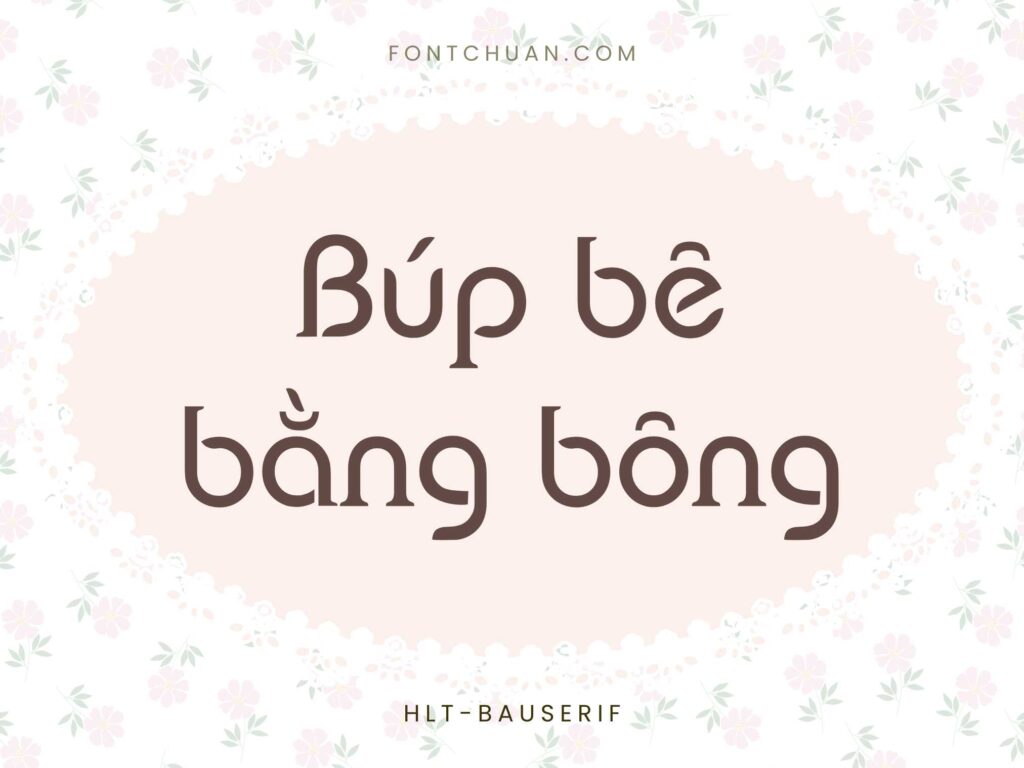
Bauserif là một phông chữ serif độc đáo, được thiết kế bởi Ayelen Arpini. Phông chữ này là kết quả của sự kết hợp giữa hai kiểu chữ: Bauhaus Medium BT và Cambria, tạo nên một thiết kế mới lạ và sáng tạo. Với sự Việt hóa của HLT, Bauserif hỗ trợ đầy đủ các ký tự tiếng Việt, giúp người dùng dễ dàng áp dụng trong các thiết kế đa ngôn ngữ. Thành viên của Font Chuẩn đã sưu tầm và chia sẻ phông chữ này nhằm đáp ứng nhu cầu đa dạng của cộng đồng thiết kế.
Về đặc điểm thiết kế, Bauserif sở hữu 262 ký tự được thiết kế tinh xảo, mang lại cảm giác hiện đại và thanh lịch. Phông chữ này đặc biệt phù hợp cho các dự án như thiết kế thương hiệu, biên tập, giao diện người dùng và các ấn phẩm quảng cáo, nơi cần sự chuyên nghiệp và tinh tế. Ngoài ra, Bauserif cũng thích hợp cho các sự kiện như lễ hội, sinh nhật, Valentine và Trung thu, tạo không khí ấm áp và gần gũi. Trong lĩnh vực ngành nghề, phông chữ này được ứng dụng rộng rãi trong quảng cáo, thiết kế thiệp cưới, giáo dục và công nghệ, góp phần tạo nên sự độc đáo và thu hút cho các sản phẩm và thương hiệu.